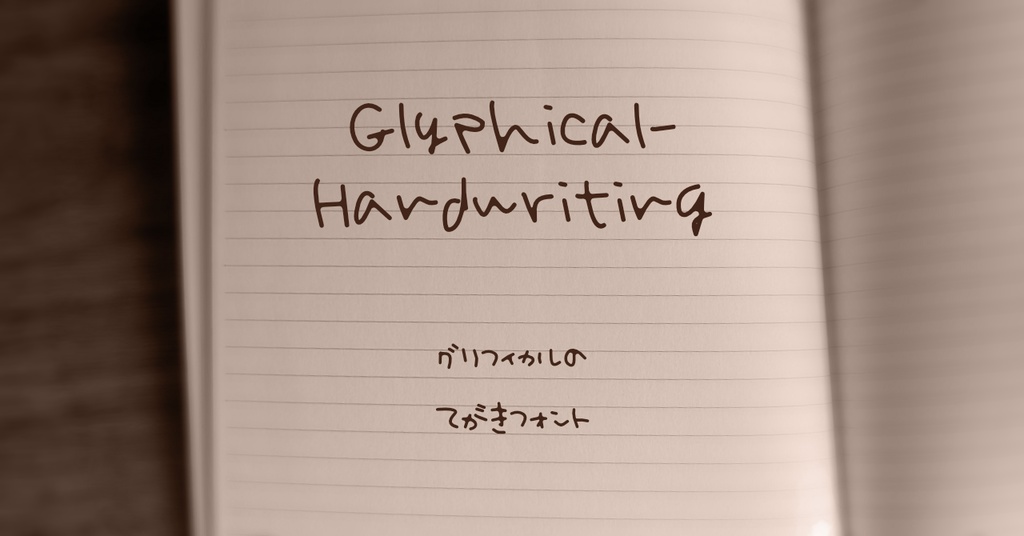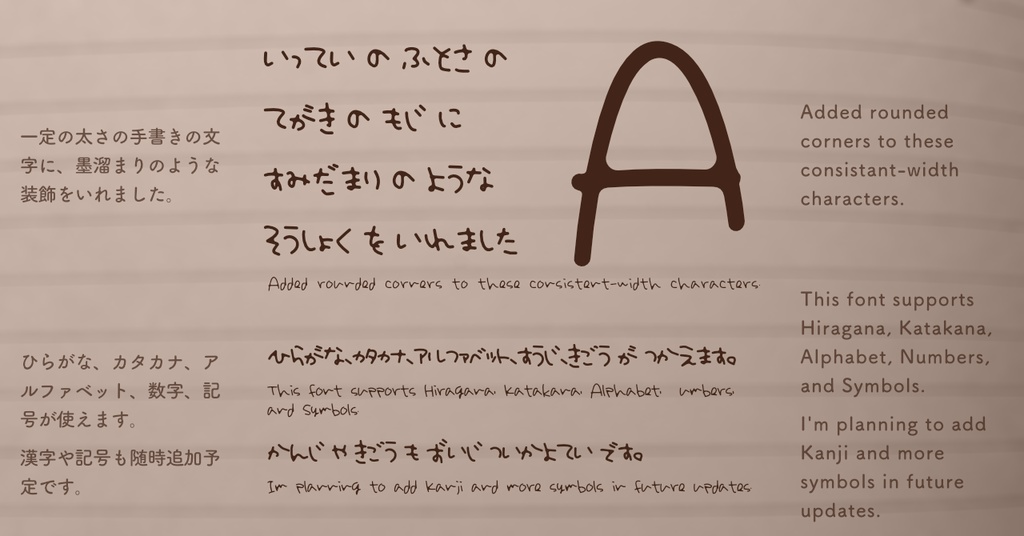
手書きフォント/Glyphical Handwriting
✎手書き文字をフォント化したフォントです。 ✎大文字、小文字、英文記号を収録。 ✎.otf形式のフォントファイルです。 ✎こちらの商品は、ダウンロード販売となっております。決済完了後、購入履歴からダウンロードが可能です。 ✦随時、漢字を追加アップデート予定です。 ✦販売形式は「現存フォント」「漢字のみ」「フルセット」の3種類を予定しています。 ✦アップデートに伴い価格を改定する場合がありますが、既にご購入済みの方は、マイページの購入履歴よりいつでも無料で最新版をDLいただけます。